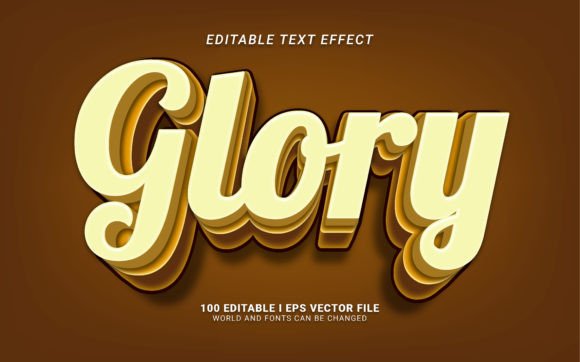
Glory Text Effect
Encontrar los elementos de diseño adecuados puede ser un desafío, pero Glory Text Effect ofrece una colección excepcional que eleva tu trabajo al instante.